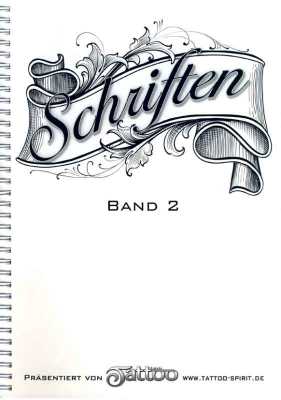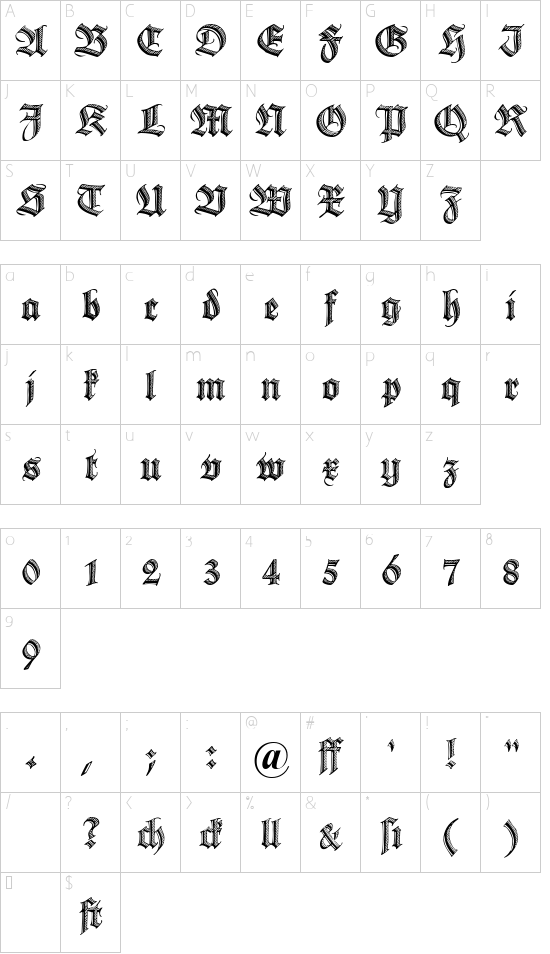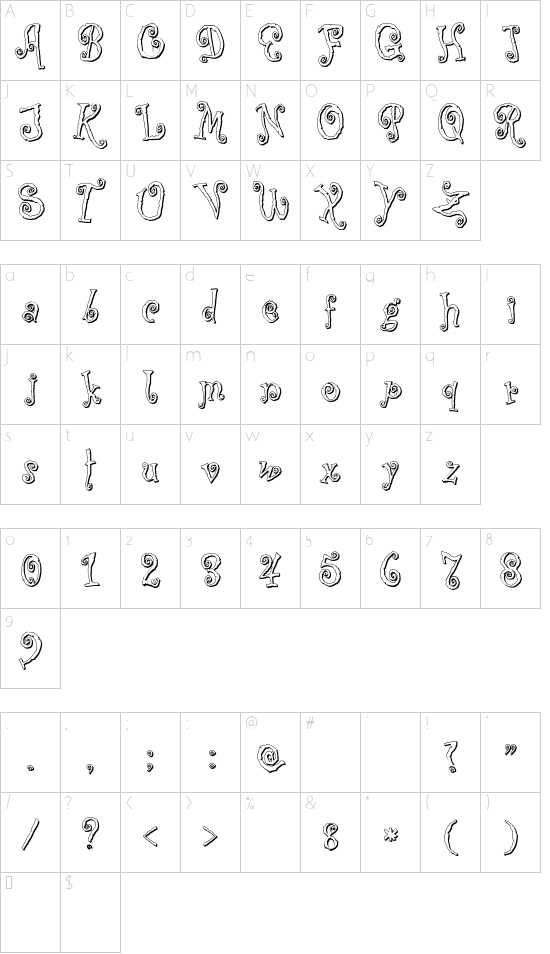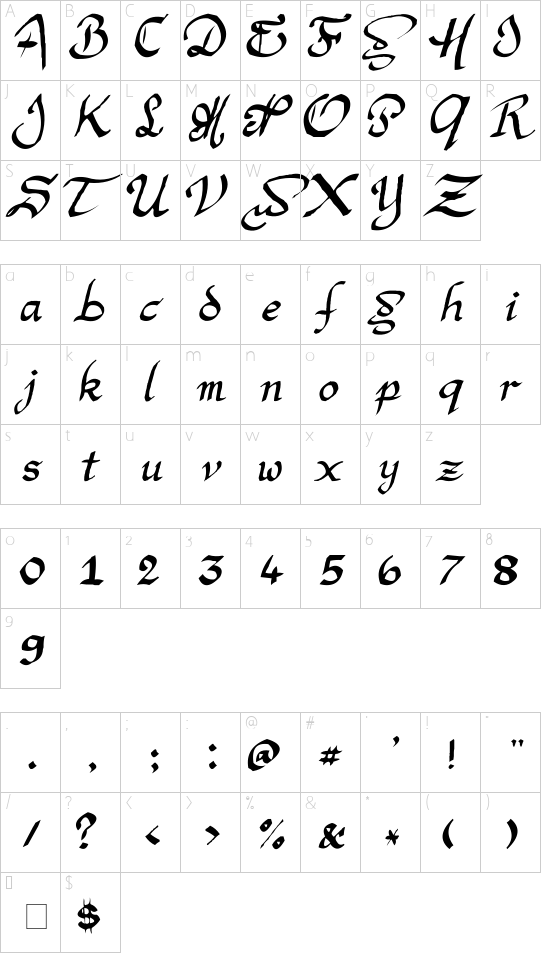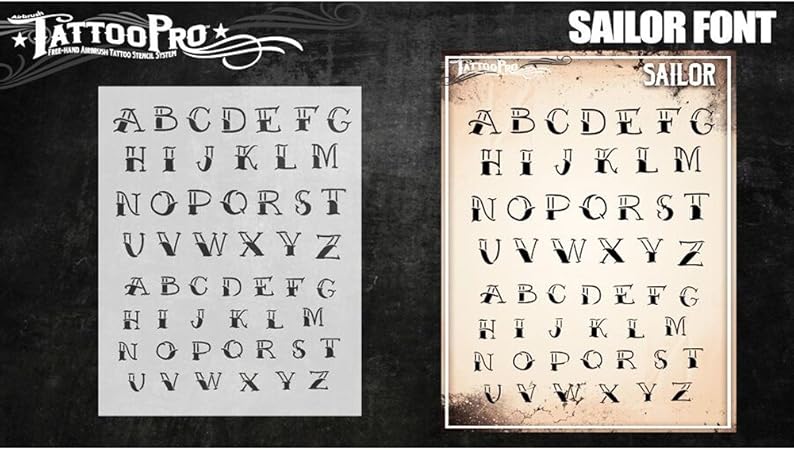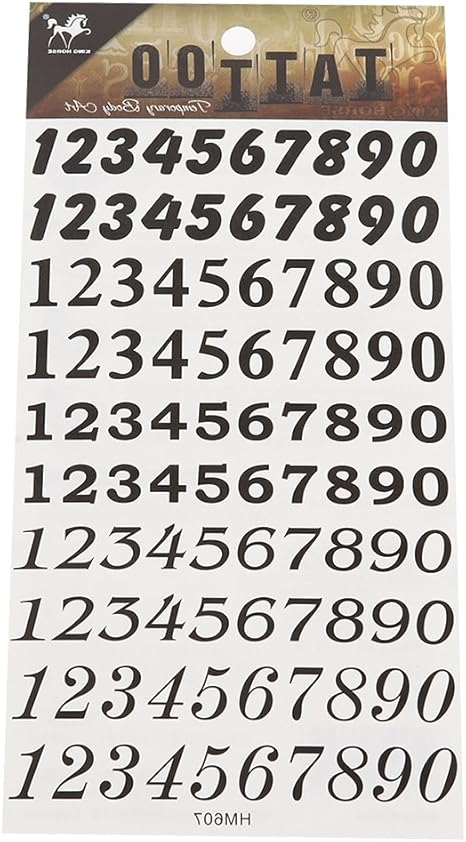
76 Zahlen Verschiedene Schriftarten Tattoo Zahlen Vorlage
07 09 2020 erkunde gideon blancos pinnwand tattoo schrift zahlen auf pinterest. Zum beispiel der tag an dem mein sohn geboren wurde hat eine besondere bedeutung für mich kann aber für andere absolut bedeutungslos sein.
Weitere ideen zu tattoo schriftzug schriftarten schrift tattoos alphabet schriftarten.
Zahlen verschiedene schriftarten tattoo zahlen vorlage. Weitere ideen zu tattoo schriftzug schriftarten alphabet schriftarten zahlen vorlagen. 19 03 2020 erkunde artur klauts pinnwand zahlen vorlagen auf pinterest. 5 vorlagen für dein römische zahlen tattoo.
Die richtige inspiration zu finden ist nicht immer einfach. 10 11 2018 erkunde mischi staus pinnwand ziffern tattoos auf pinterest. 19 03 2020 erkunde artur klauts pinnwand zahlen vorlagen auf pinterest.
Weitere ideen zu zahlen tattoos schrift tattoos tattoo schriftzug schriftarten. Kalligraphie schriftarten sind ideal als blickfang und eignen sich vor allem in überschriften oder als statement schriftart. Weitere ideen zu schrift tattoos tattoo schriftzug schriftarten für tattoos.
Weitere ideen zu tattoo schrift zahlen tattoo schrift tattoos. Das datum tattoo zählt zu den klassikern unter den. 24 05 2020 erkunde chriss pinnwand zahlen tattoos auf pinterest.
Viele kunden entscheiden sich für ihren hochzeitstag oder der tag an dem sie mit ihrem partner zusammengekommen sind oder abschlusstag. Wir haben dir fünf beispiele herausgesucht die zeigen dass ein tattoo mit römischen zahlen ganz unterschiedlich aussehen kann. Wir stellen dir 23 schöne und kostenfreie kalligraphie schriftarten vor die du direkt in canva nutzen kannst von simpel bis verschnörkelt zierlich bis auffällig traditionell bis modern.